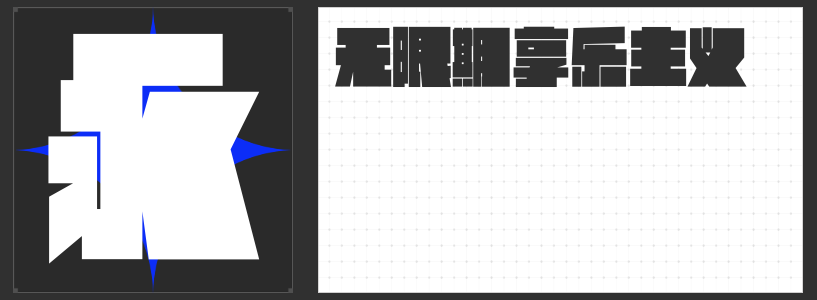
创意设计新势力:四款突破性字体的视觉革新之道
在当代设计语境中,字体的选择早已超越信息传递的基础功能,成为塑造品牌个性、强化视觉张力的核心元素。本文精选四款兼具艺术性与功能性的创意字体,它们以突破性的结构创新与美学表达,为设计师提供全新的创作维度。
一、励字逆反差圆舞简·超级黑
这款字体以逆反差美学重构传统黑体的视觉逻辑,通过弧线与直线的戏剧性碰撞,创造出软硬交融的动态平衡。饱满的弧形笔画(如撇、捺、钩)与硬朗的直线框架形成强烈对比,中宫舒展的设计确保了阅读流畅性,而对称的笔画布局则赋予文字庄重感。其独特的张力既适用于科技品牌的未来感表达,也能为文化类项目增添灵动气质。
二、励字宽边黑简·超级黑
通过非对称的笔画粗细对比(右部加粗/左部纤细),这款字体颠覆了传统黑体的均衡美学,形成极具吸引力的视觉向心力。方正的字型框架中,横竖笔画的粗细反差强化了力量感,而减细的左侧笔画则巧妙平衡了整体重量。这种“矛盾美学”使其成为运动品牌、潮流视觉的理想选择,能在静态画面中营造动态势能。
三、高手庆科智雅体 大黑
以极简主义为设计哲学,这款直线字体通过精准的切口处理与布白控制,构建出秩序感强烈的视觉系统。横竖笔画等粗设计消解了传统黑体的机械感,而灵动的连笔折笔则赋予文字呼吸感。中英文符号的协同设计尤为突出——西文字母延续中文的切角折笔特征,形成跨语言的一致性表达,适合国际化品牌的高端视觉呈现。
四、高手字斋东京体
从传统书法中提炼现代基因,这款字体以等宽方块结构重塑汉字形态。锋利的笔画切角与光洁的曲线形成微妙对抗,既保证了远距离的视觉冲击力,又通过平滑的轮廓传递亲和力。符号系统深度融合形意关系,使整套字体形成自洽的美学宇宙,特别适用于文化创意、生活美学类项目的深度表达。
这四款字体通过结构解构、笔画创新与美学重构,为设计注入新的可能性。它们不再是被动的信息载体,而是成为视觉叙事的主角,在品牌塑造、空间设计、数字交互等领域持续释放创意能量。